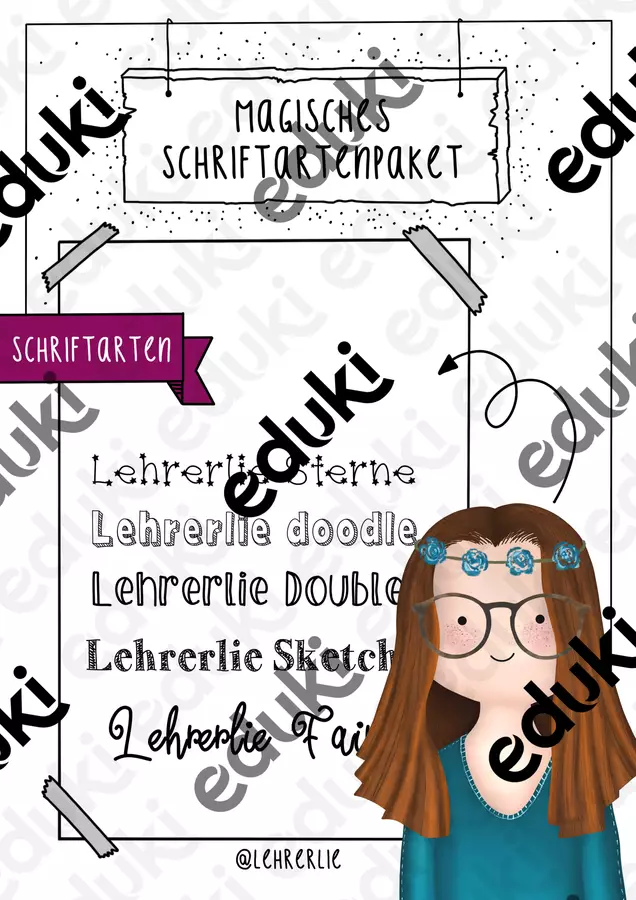
Dieses Paket enthält viele tolle Schriftarten, die sich wunderbar zum ansprechenden Gestalten von Überschriften auf Arbeitsblättern eignen. Nach und nach werden weitere Schriftarten hinzugefügt!
Achtung: Nicht alle Schriften enthalten alle Zeichen! Die meisten beinhalten die Standard-Schriftzeichen, einige wenige aber nicht vollständig - deshalb konzentriert sich dieses Paket auf die Gestaltung von Überschriften. :-)
Magisches Schriftartenpakt - 5 Schriftarten // Überschriften
Tolle Schriften, nutze sie super gerne. Leider funktionieren einige Buchstaben bei mir nicht (weil nicht verfügbar?), so das ä, ö, ü, ß. Das ist etwas schade. Aber sonst wirklich top :-)
Hallihallo, gibt es für die Verwendung von ö, ä, ü etc. einen besonderen Trick? =)